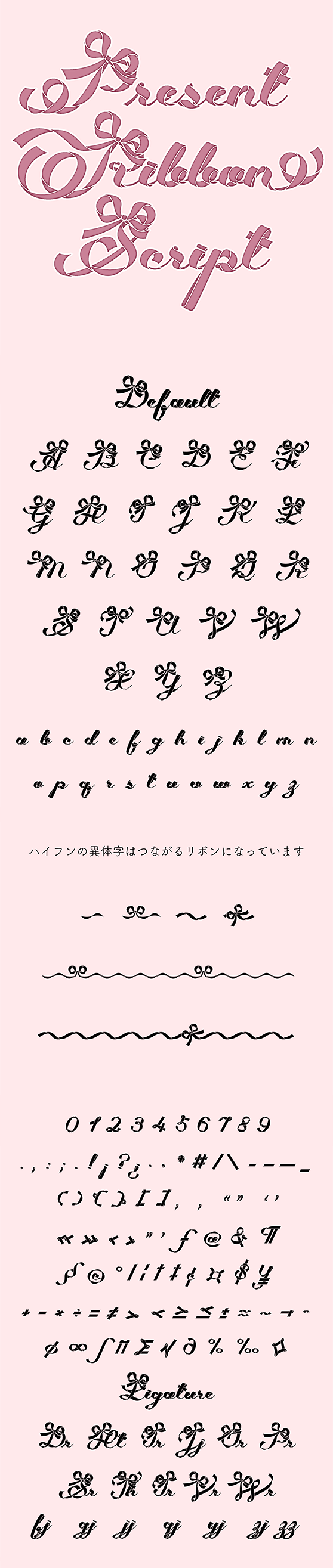
Satsuyako
Present Ribbon Script
リボンの筆記体が打てるフォントです。記念日や誰かへのメッセージなど、特別感を出したい場面でラッピングのように飾り付けるというコンセプトで作りました。
ひとつのフォントファイルの中にデフォルト字形 + 異体字(大文字5種類、小文字の異体字8種類)を収録していて、Adobeアプリで簡単に切り替えることができます。
・基本ラテン文字
・約物
・記号類 ( 一部 )
・大文字の異体字ss01~ss05
・小文字の異体字ss01~ss08
・リガチャ